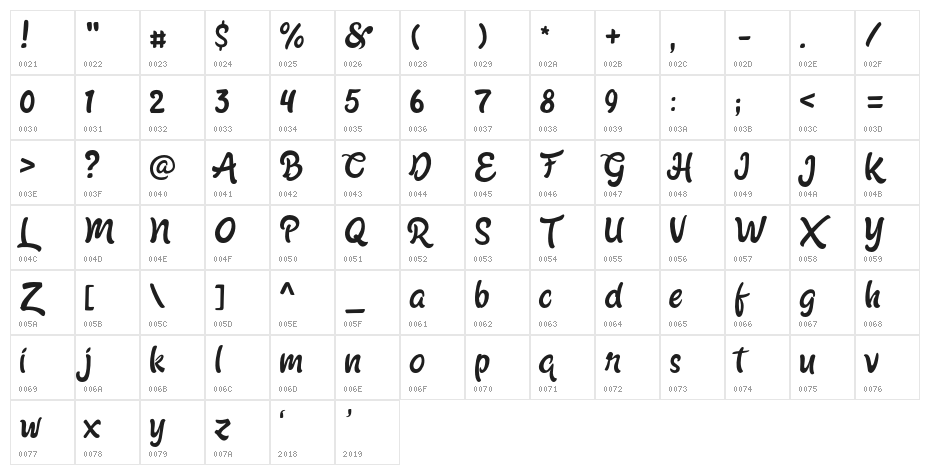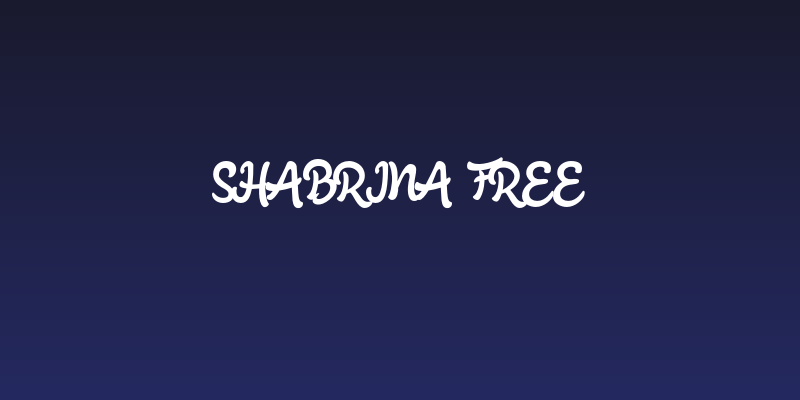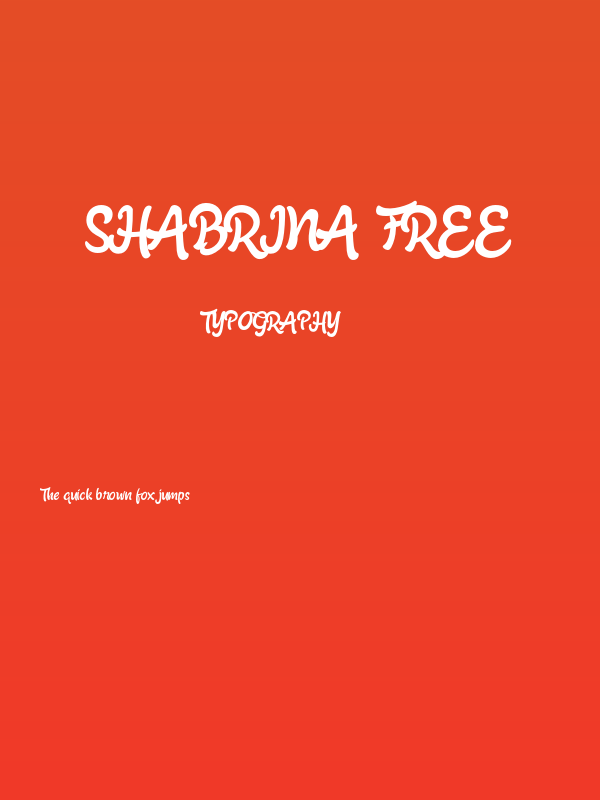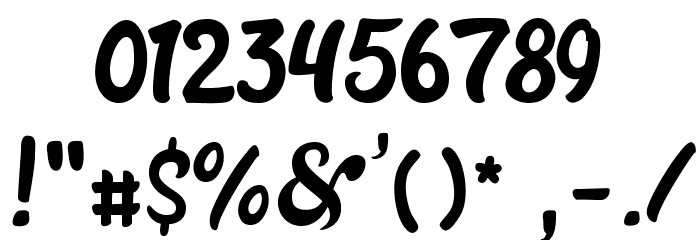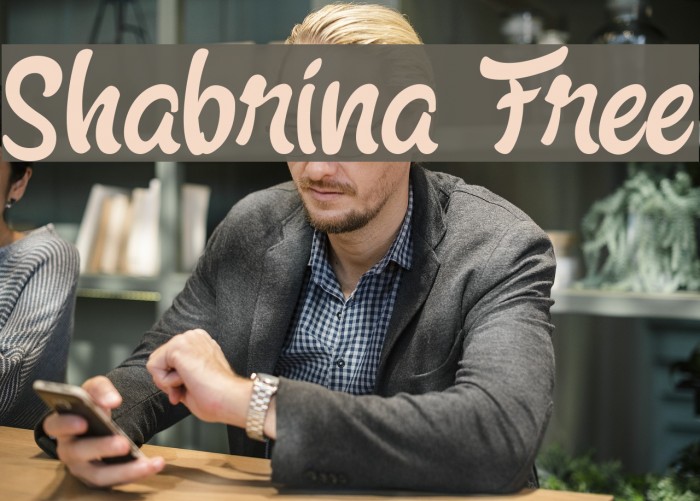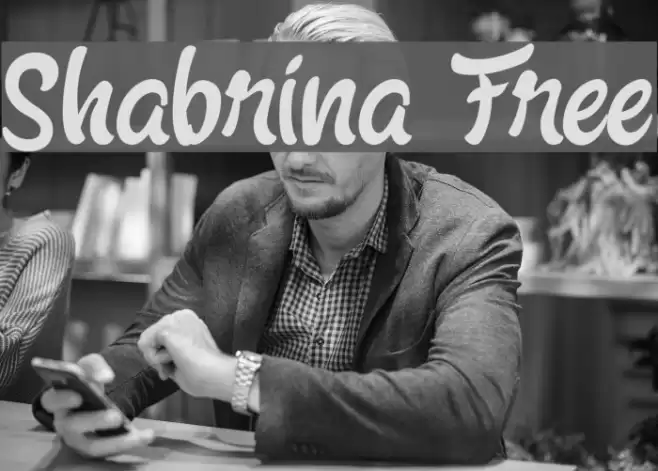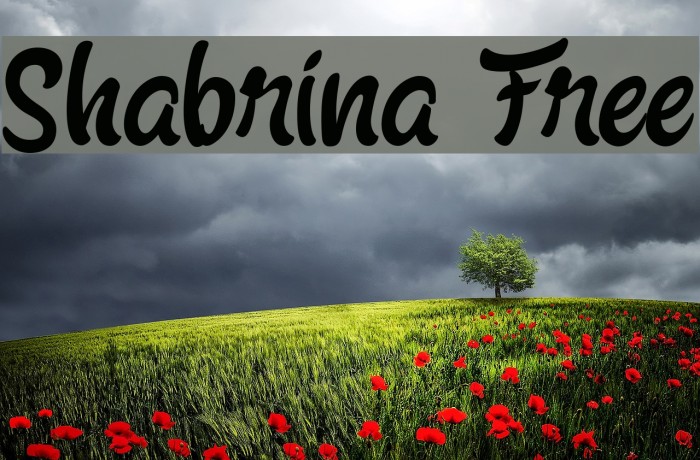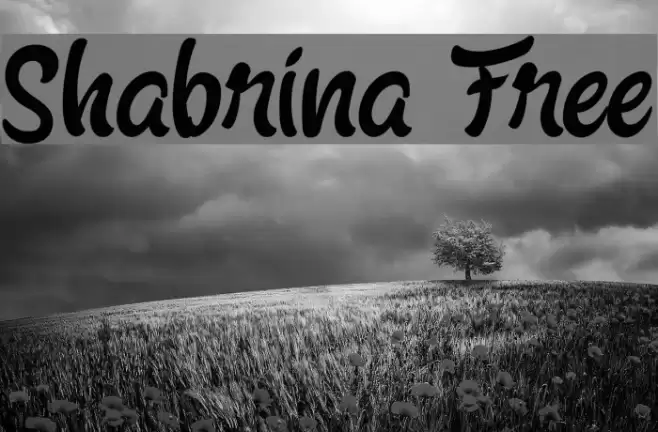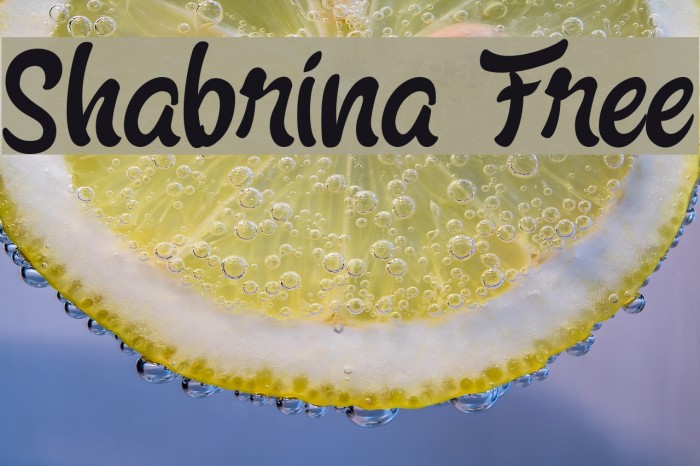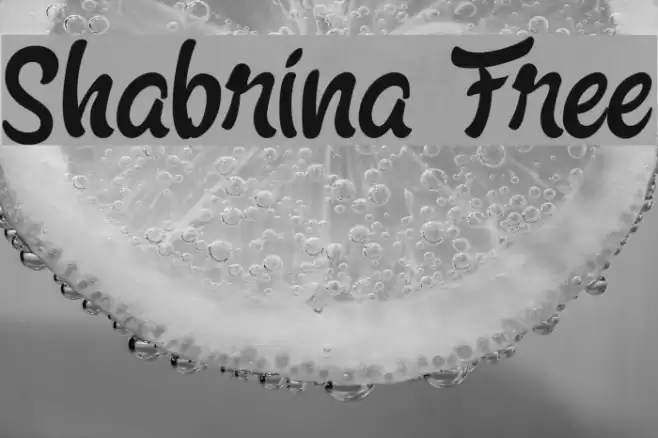
Shabrina Free Font
| Estilo general | Playful, Creative |
| Caso de uso | Logos, Headlines, Invitations |
| Proyectos propuestos | Ideal for greeting cards, invitations, playful branding, and creative posters. |